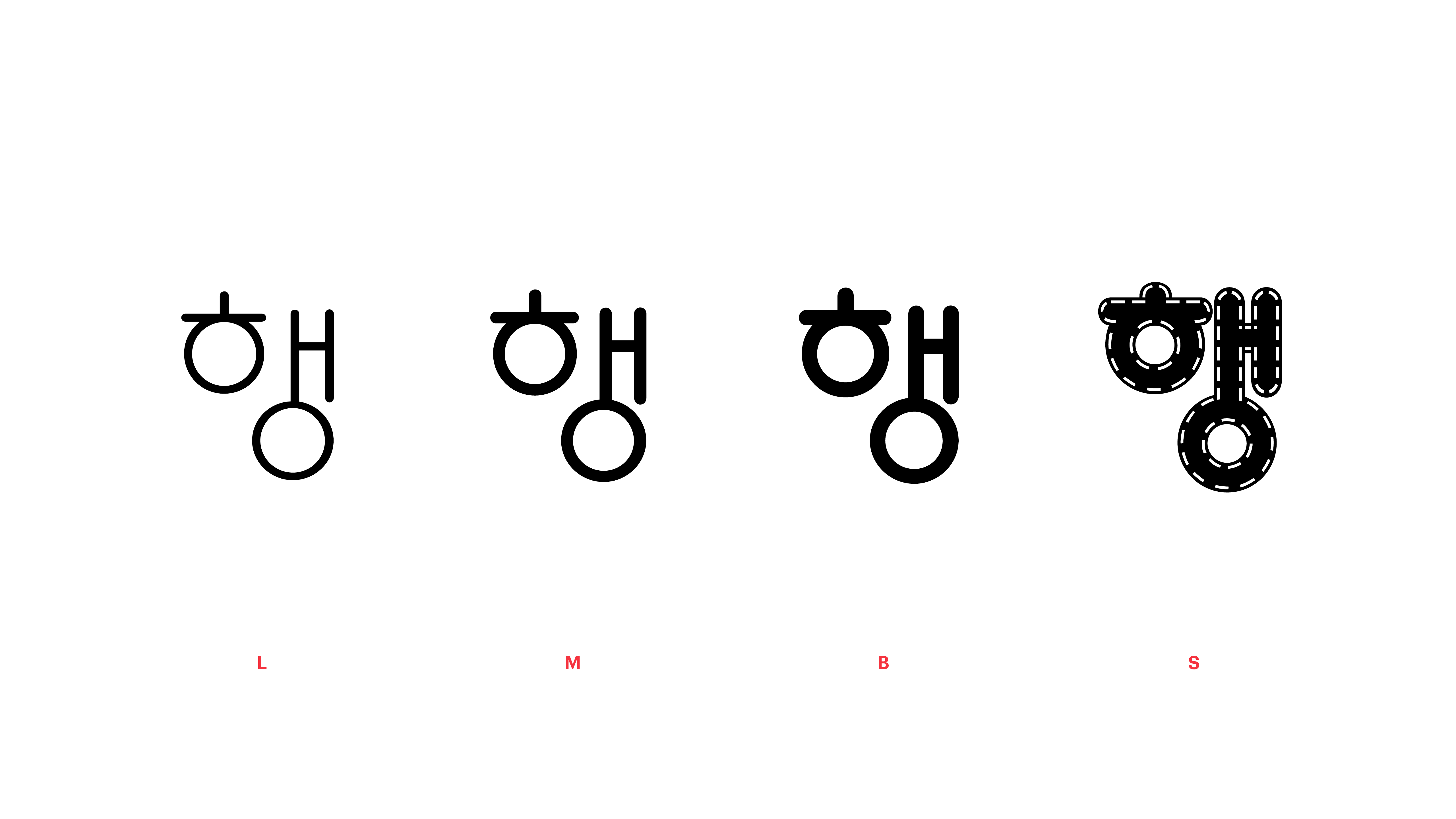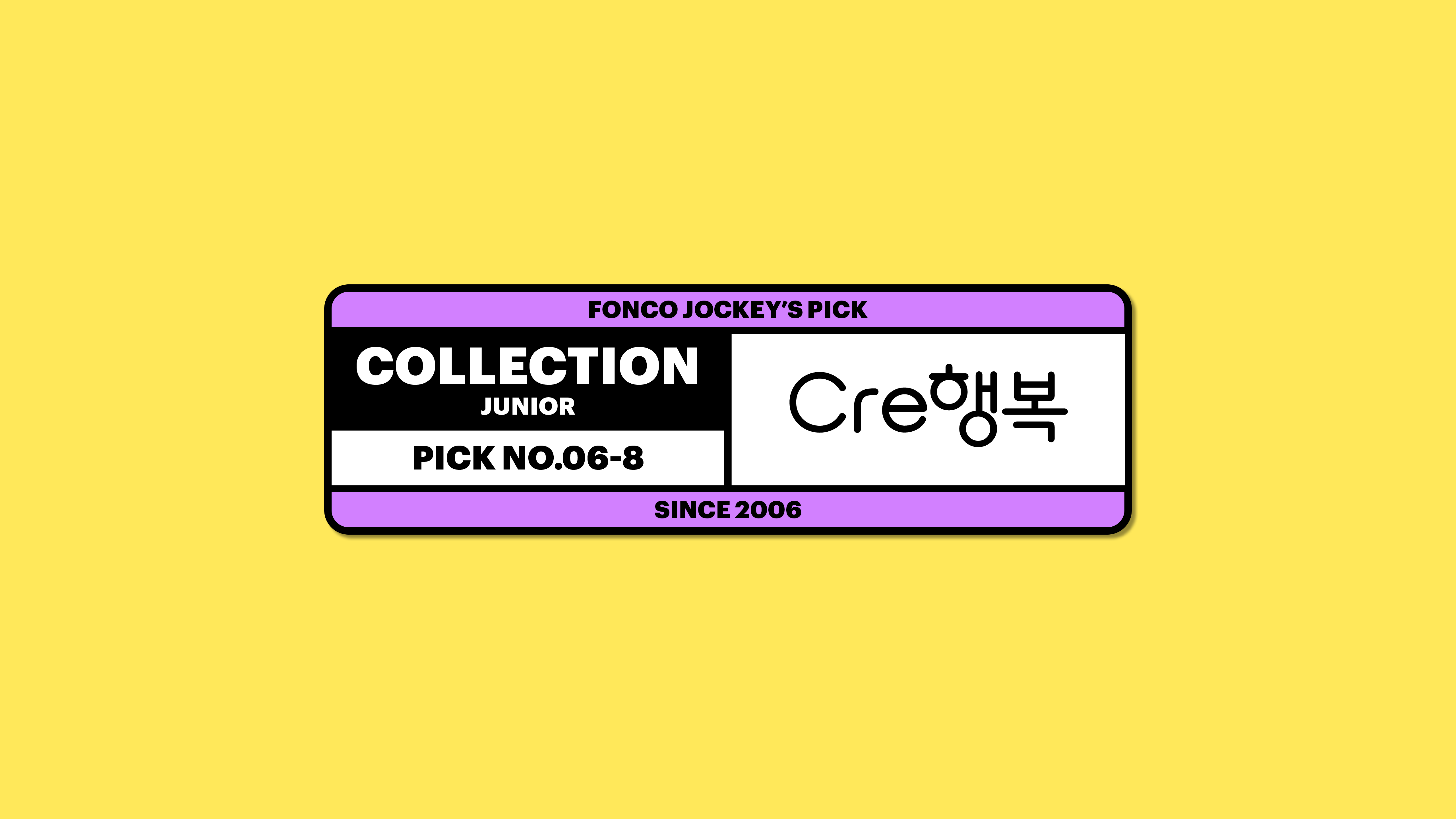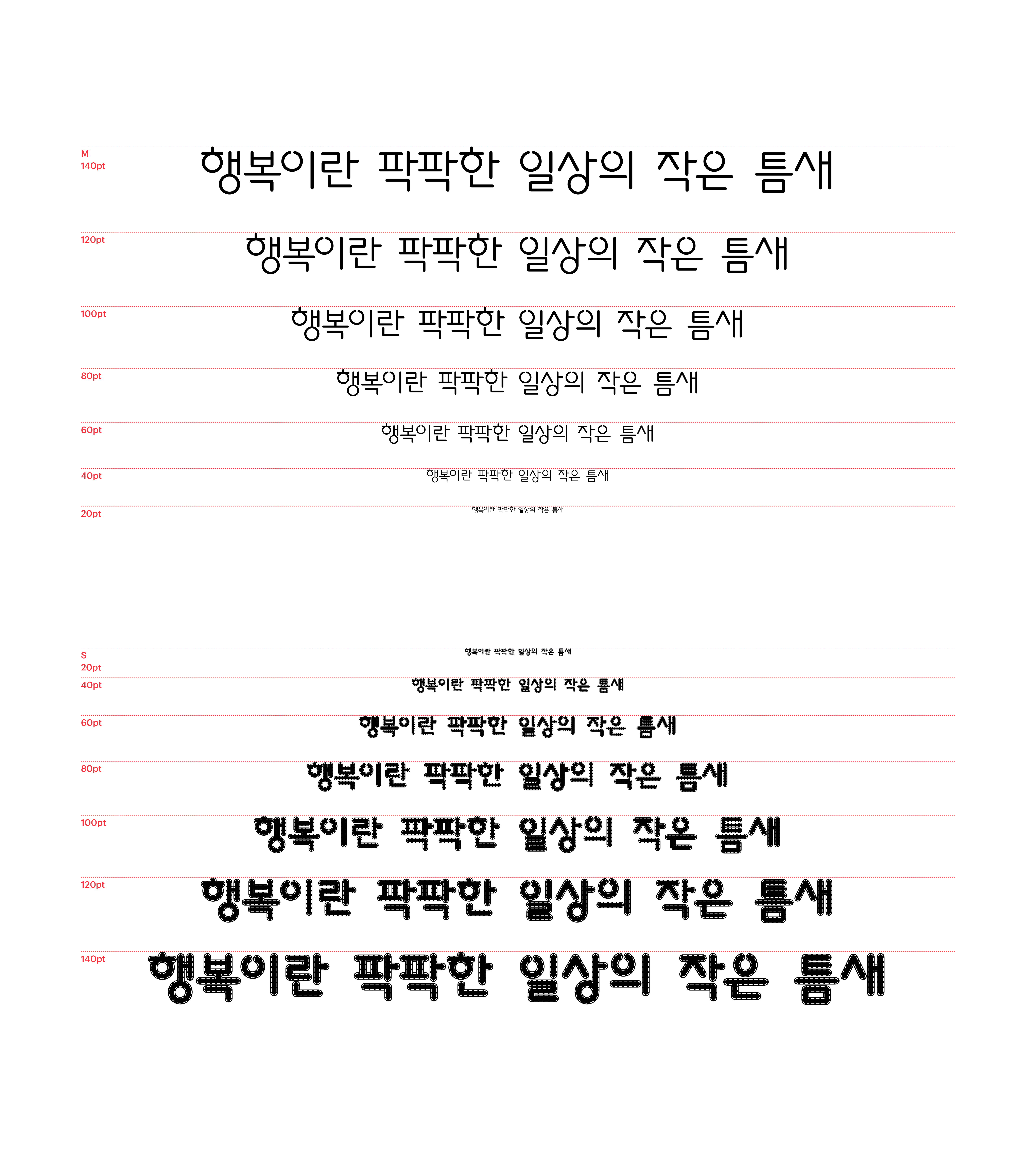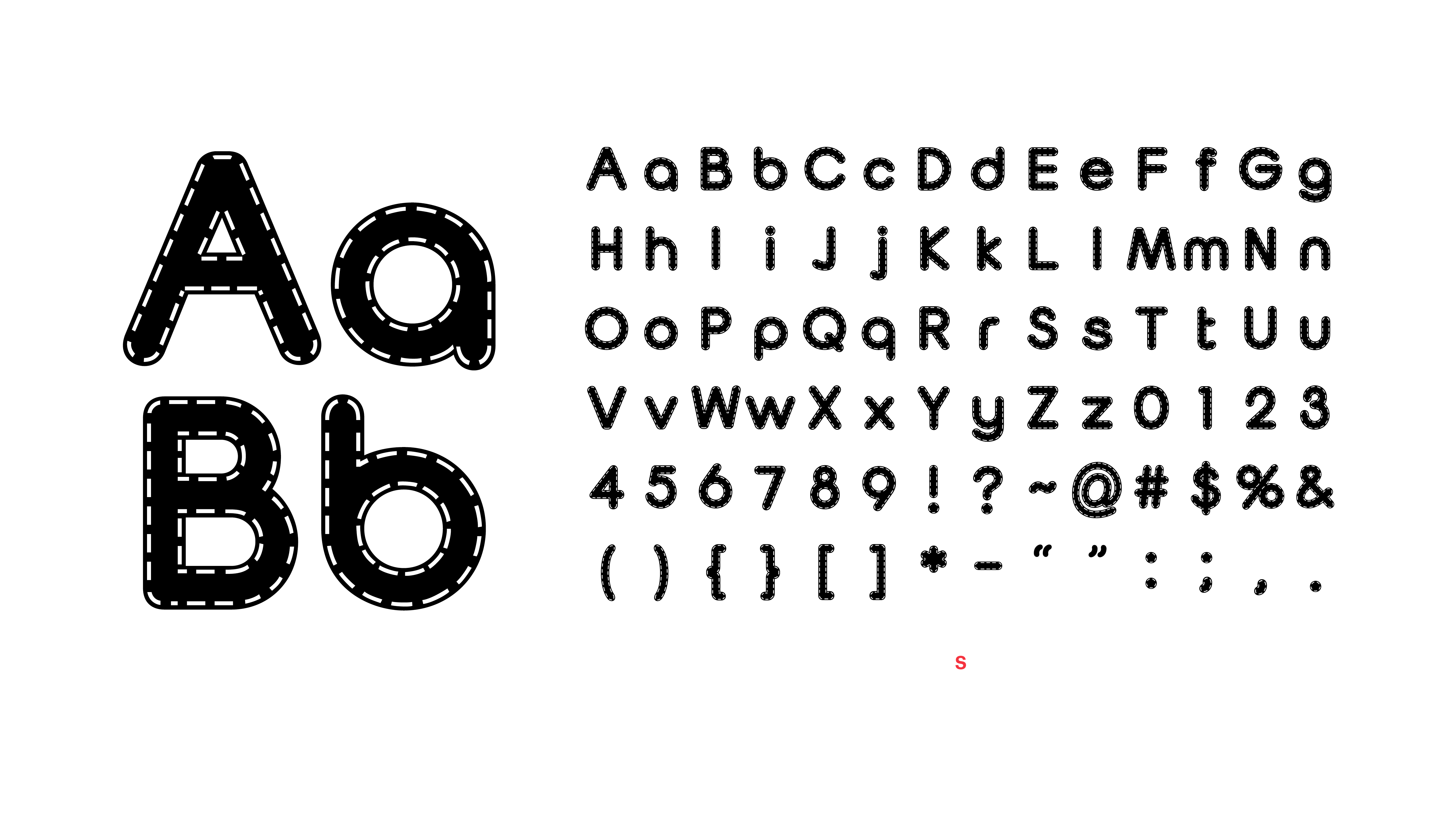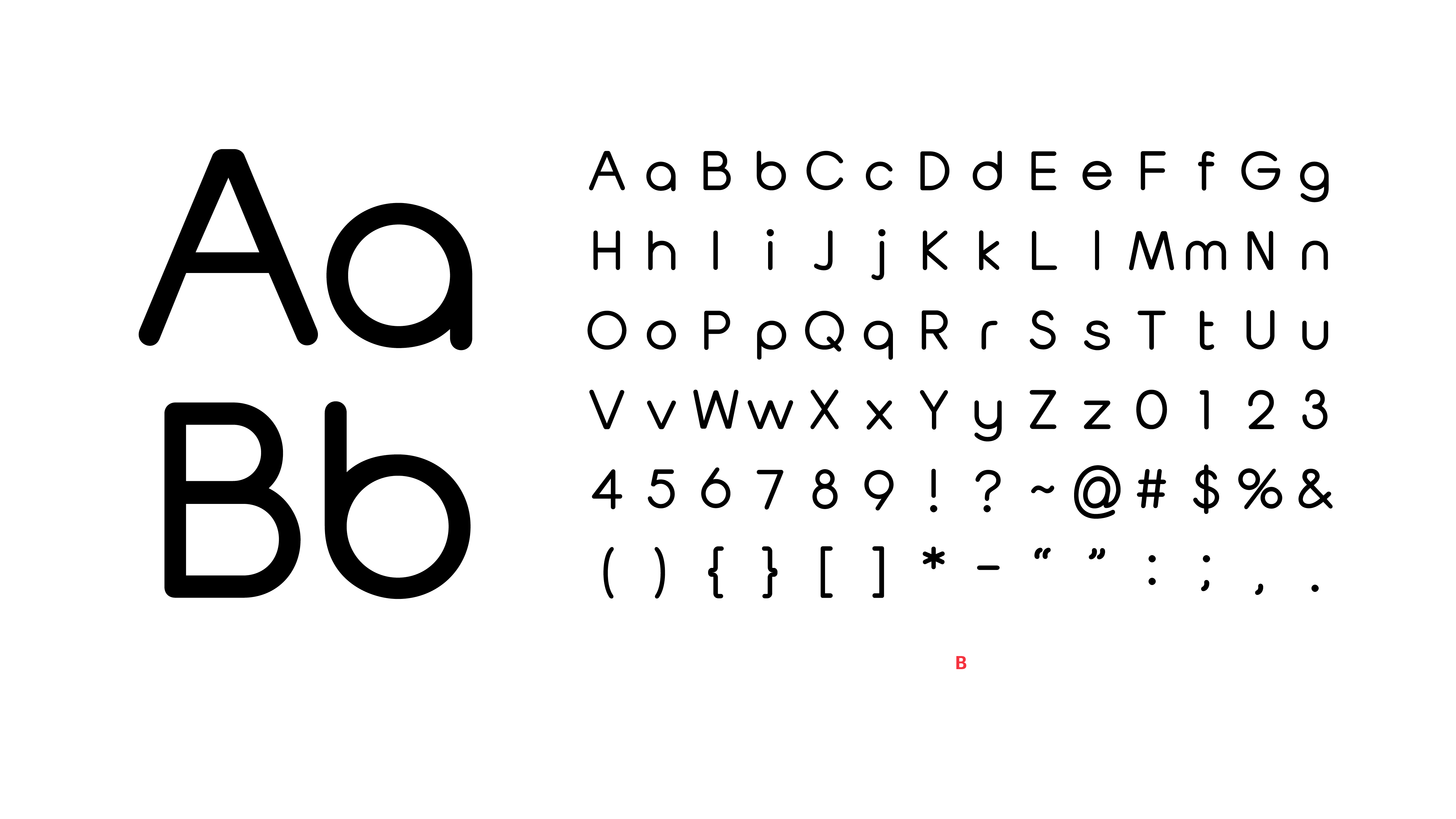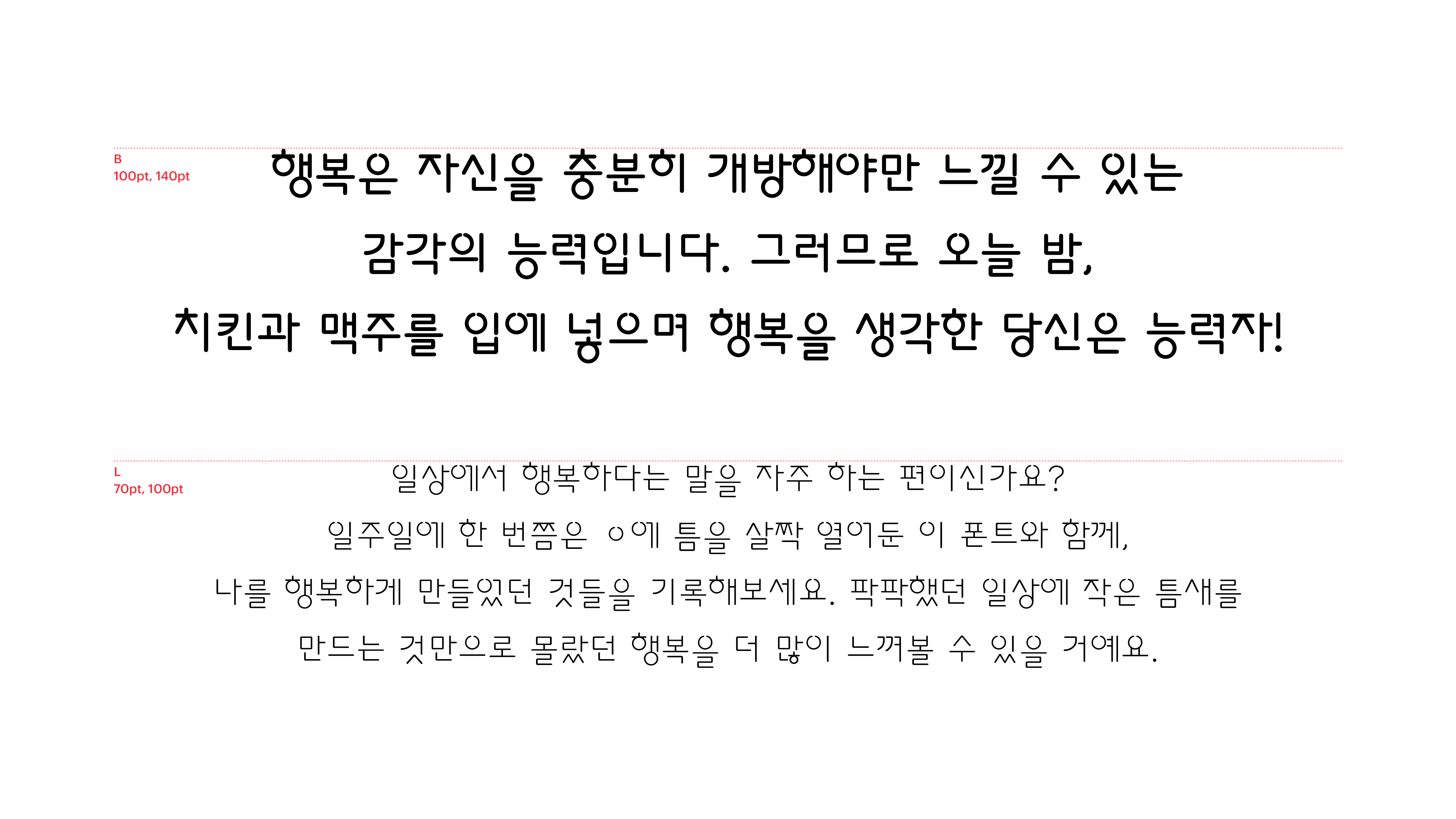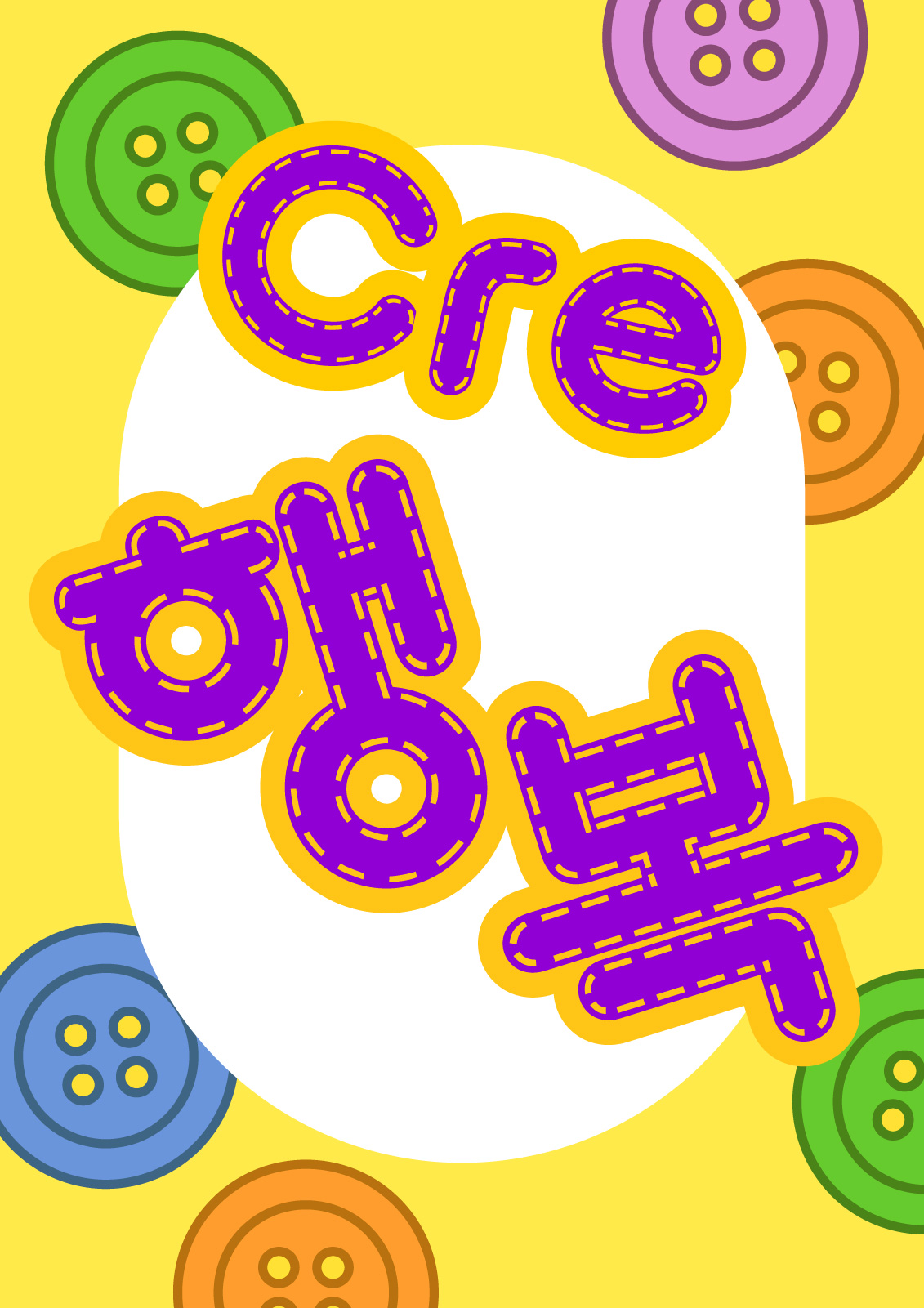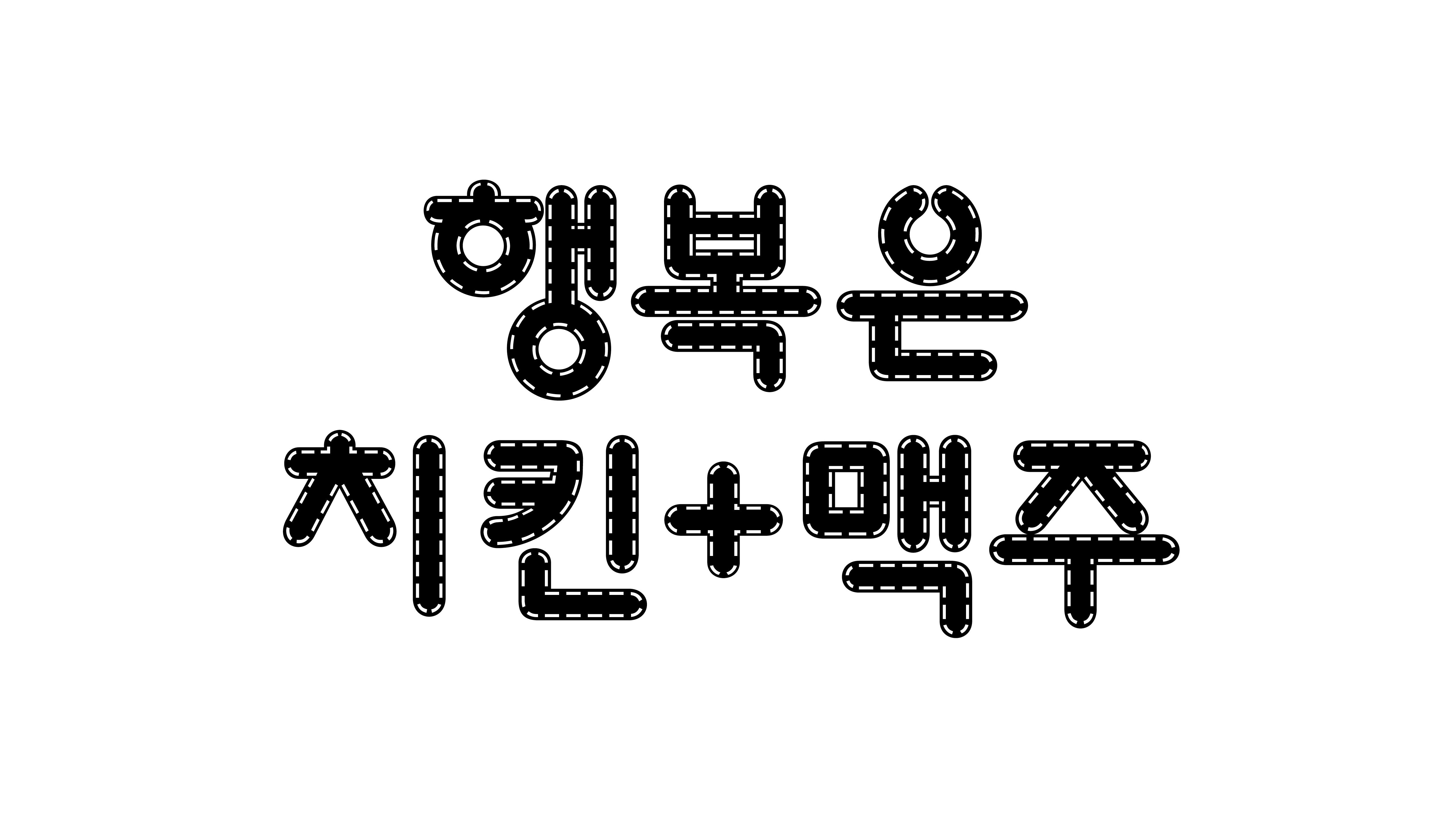
Cre 행복
Yoon Cre행복
일상에서 행복하다는 말을 자주 하는 편이신가요? 일주일에 한 번쯤은 ㅇ에 틈을 살짝 열어둔 이 폰트와 함께, 나를 행복하게 만들었던 것들을 기록해보세요. 팍팍했던 일상에 작은 틈새를 만드는 것만으로 몰랐던 행복을 더 많이 느껴볼 수 있을 거예요.